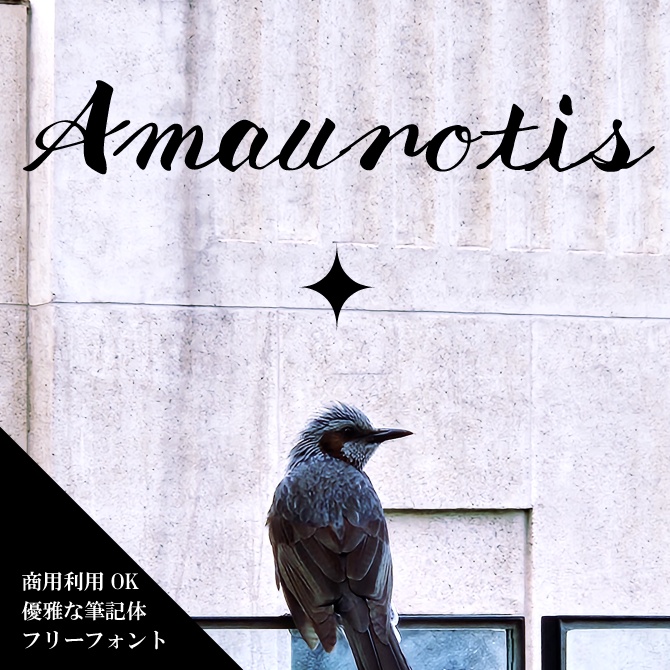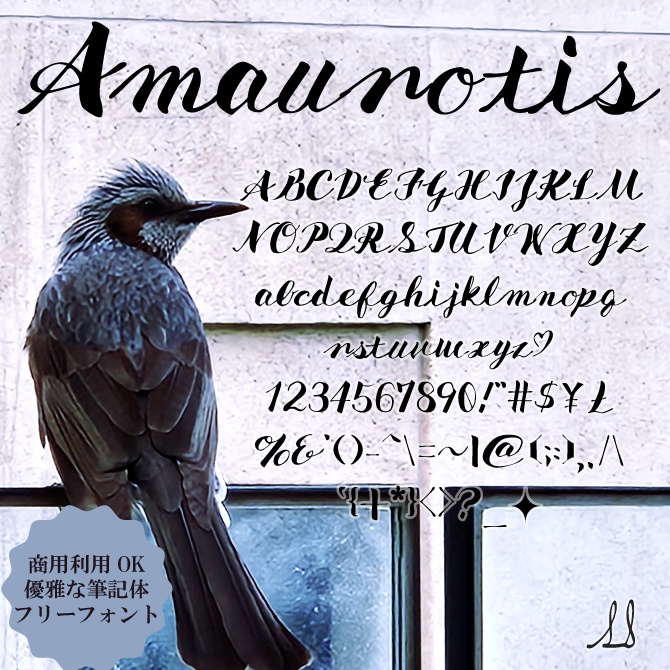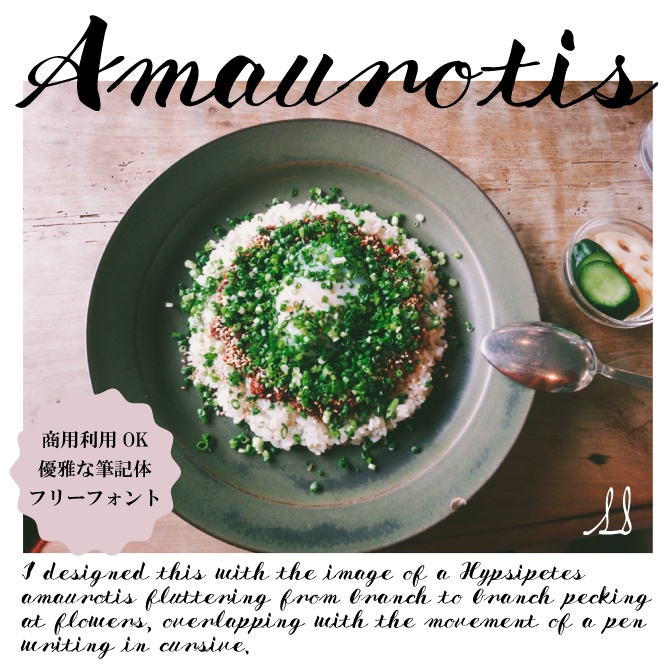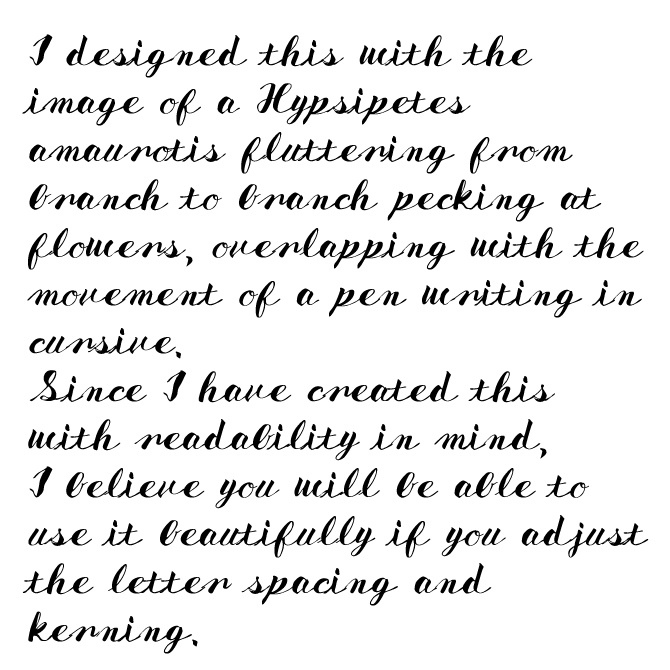
筆記体ではありますが一文字ずつの読みやすさを意識して制作しています。文字の詰めなどを工夫していただくとなめらかに使用して頂けると思います。インクだまりが少しあるので、レトロな印象にもなります。花をついばみ枝から枝へと飛びまわるヒヨドリの姿と、筆記体を書くペンの運びにイメージを重ねて名づけました。 Although it is a cursive script, I have created it with a focus on the readability of each individual character. You can achieve a smoother look by adjusting the letter spacing as needed. It has slight ink bleeding, which gives it a retro feel. I named it after the image of a brown-eared bulbul pecking at flowers and flitting from branch to branch, which I associate with the movement of a pen when writing in cursive. ひよどりの こぼし去りぬる 実の赤き / 与謝蕪村